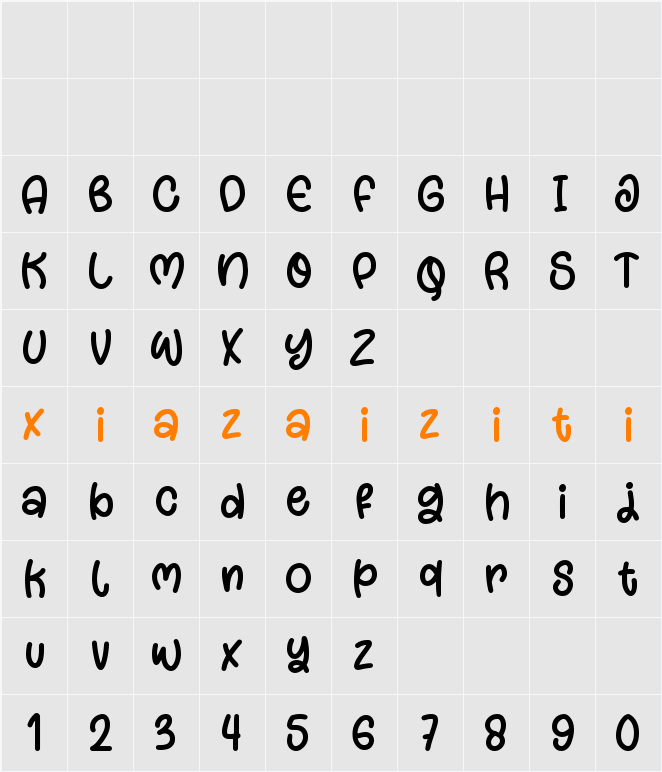
Winter Feast
Winter Feast,这款字体结构工整、笔画清晰,兼顾美观与易读性,适用于标题、正文、海报、包装、LOGO 等多种场景。字形优雅稳定,风格百搭耐看,适配日常排版与创意设计,让文字呈现更舒适、更具质感。Winter Feast一笔一画,皆是细节,以均衡的比例、流畅的线条打造舒适视觉体验,字形端正大气,风格简约现代。无论是商业设计、品牌宣传还是日常排版,都能轻松驾驭,让文字更有格调与力量。Winter Feast字体下载。